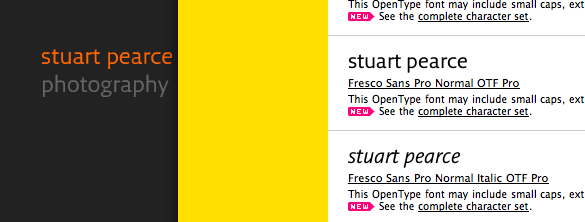
Nicht die Fedra Sans . . .
vista sans
Die Vista Sans ist das nicht: e und c laufen in der Vista Sans viel enger – g und y haben auch andere Formen. :neenee:
stimmt. mit dem a kann es aber nur von xavier dupré sein. :-)
das hab ich beim ersten Hinschauen auch gedacht. Habe eben alle Schriften die ich von ihm finden konnte durchgeschaucht, aber diese eine ist nicht dabei. :twisted:
Hat vielleicht sonst noch jemand eine Idee? :wink:
Vielleicht eine Fresco Sans von Fred Smeijers (Ourtype)? oder ist die auch bloß ähnlich?
ist ja witzig: der Anstrich vom »a« wird in Flash zu einer Geraden. Daher die falsche Fährte zu Xavier. Gute Nase, Norbert